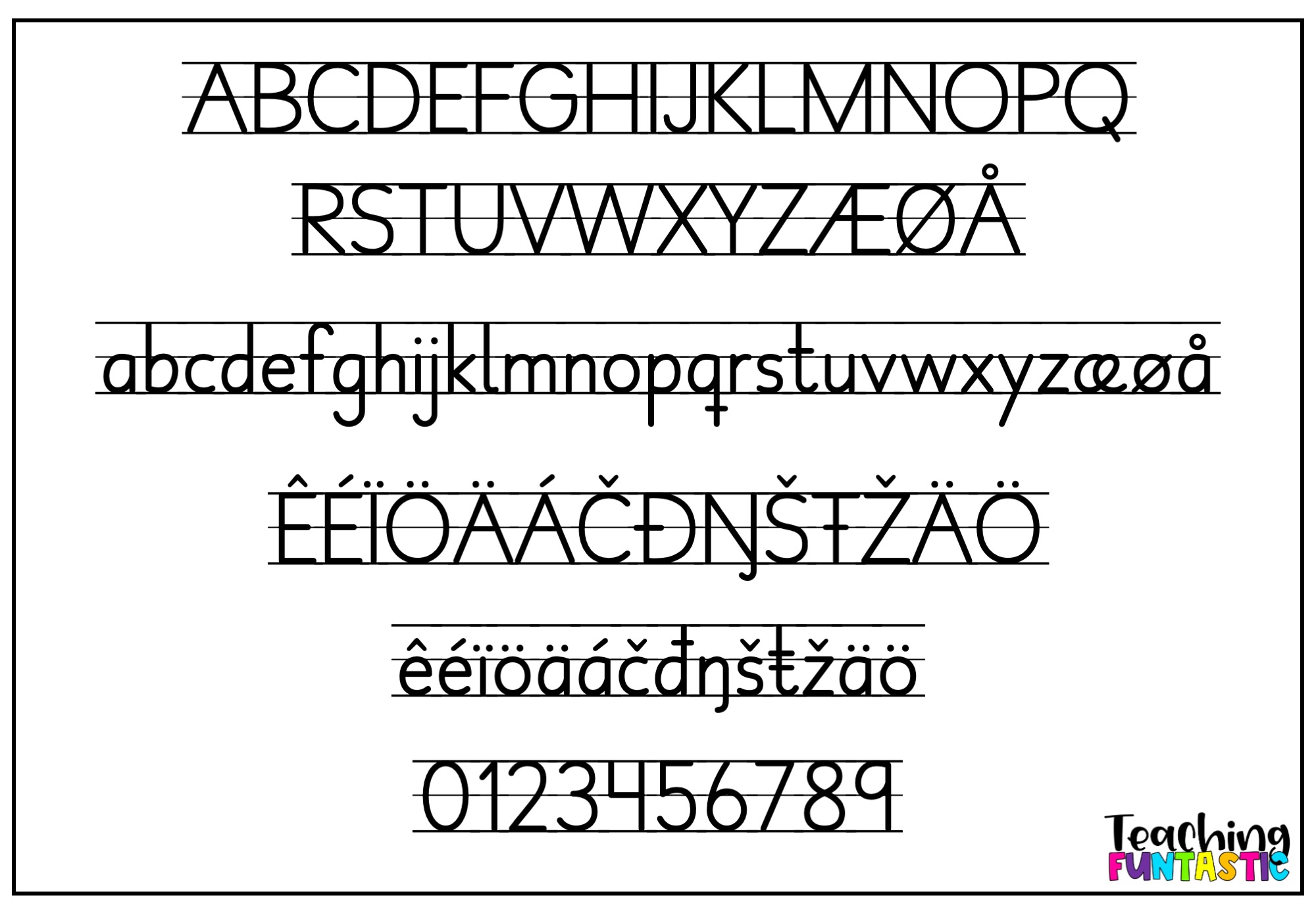
FUNtastic Trykkskrift 1 Bokstavhus – en font til trening av håndskrift
Funtastic Trykkskrift 1 – Bokstavhus er en linjert versjon av FUNtastic Trykkskrift 1, der bokstavene automatisk plasseres i et ferdig bokstavhus med hjelpelinjer. Perfekt til oppgaveark, skriveøvinger og bokstavforming i begynneropplæringen!
Denne fonten gjør det enkelt å lage skrivetreningsark uten behov for å sette inn linjer selv – bare skriv rett i Word eller PowerPoint, så vises bokstavene med riktige linjer, som et bokstavhus.
Perfekt for skrivetrening i begynneropplæringen
Når barn lærer å skrive, er det viktig at de øver med tydelige, gjenkjennelige bokstavformer. Med denne fonten kan læreren raskt lage tilpassede oppgaver som bokstavark og skriveøvelser. Elevene får øve både motorisk og visuelt, med bokstavformene de ellers lærer å lese og skrive. Det gir trygghet og mestring i skriveprosessen – spesielt for elever som trenger mer støtte i finmotorikk og bokstavenes plassering.
En font håndskrift laget for lærere
FUNtastic Trykkskrift 1 Bokstavhus er enkel å installere og bruke i PowerPoint, Word eller Canva Pro. Den gir deg full frihet til å designe oppgaver som passer akkurat din klasse. Fonten er utviklet som lesbar font for barn, og passer perfekt til alt fra bokstavforming og finskrift til skrivetrening.
Norsk font med alle bokstaver
Fonten inkluderer alle de norske og samiske bokstavene. Bokstavene har balansert høyde og avstand for best mulig lesbarhet, både på skjerm og utskrift.